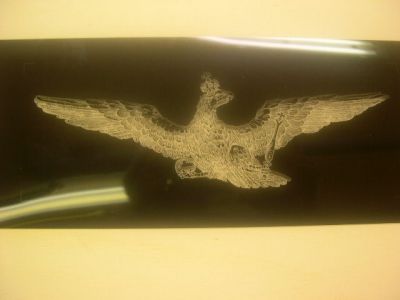
Ich studiere visuelle Kommunikation in Bern. Heute haben wir den Auftrag bekommen uns ein beliebiges Forum aus dem Netz zu nehmen und es in die Form eines Buches zu bringen (wird natürlich nicht veröfentlicht!). Da hab ich mich mal umgeschaut und dieses Forum als passend empfunden.
Nun denn. Wenn jemand Lust und zu viel Zeit hat, kann er mir eine Buchcover gestalten. Ich stelle mir natürlich eine typografische Umsetzung vor. Als super mega Belohnung stelle ich dem besten ein Buchexemplar zu. :-)
Würde mich über Ideen freuen!!
:shock: WÄre das nicht eher Deine Aufgabe?
Nein, wir wurden auserwählt, das ist jetzt unser Problem ...
Im Ernst: Die Idee finde ich interessant (wobei ich nicht genau weiß wo man da anfangen und aufhören soll. Ein klassisches Buch ist ja meistens etwas Abgeschlossenes).
Man könnte natürlich hier die spannendsten Diskussionen zusammentragen und diese in Buchform bringen. Das wäre wohl am lohnenswertesten.
Zum Cover: wenn du, Benjamin, hier Entwürfe reinstellst werden sie sicher kommentiert werden. Aber machen wird dir das wohl kaum jemand.
Spaß bei Seite.
Welchen Umfang soll das Buch denn haben?
Ansonsten finde ich die Idee ganz interessant.
Ein Querschnitt aus einem Fachforum, ordentlich mit Quellen versehen (ja, ich weiß, ich wiederhole mich) und einige der ja durchaus manchmal spannenden Diskussionen aufzeigend... warum nicht.
Ich könnte einen Andruck bzw. einen Negativ-Film von einem Kaiser-Adler mit Krone beitragen...
Oder, wenn Euch das zu wuchtig ist... mir schon, ich bin ja kein Monarchist... dann fallen mir bestimmt noch einige andere nette Entwürfe ein :)
Aber die Frage ist natürlich berechtigt:
Warum machst Du die Gestaltung nicht selbst?
slanted druckt ja auch immer einen teil ihres blog im mag ab,
ich finde das eher uninteressant, vorallem weil immer solche
blöden unbrauchbaren kommentare von xxx und mir dazwischen
stehen.
den titel machst du mal schön selbst und zeigst ihn uns danach,
wir müssen das immerhin absegnen.
Alle Quellenangaben werden drin sein und natürlich werde ich euch auch eine digitale Version ins Netz stellen!
Das Buch soll einen Umfang von 100-200 Beiträgen haben. Also nicht sehr gross. Den Dozenten geht es in erster Linie natürlich auch nicht um den Inhalt sondern um die Darstellung. Wegen dem Buchcover, ist wohl wirklich meine Aufgabe obwohl der Negativ-Film von einem Kaiser-Adler mit Krone gefällt mir schon ganz gut. Aber das kann doch noch nicht alles sein. :-)
Höhö...
Geschickt gemacht. Du spekulierst jetzt darauf, daß die Jungs hier ums Verrecken vermeiden werden, daß Dein Typoforum-Buch einen schönen, nationalen Charakter bekommt und deshalb Gegenentwürfe vorlegen, richtig? :twisted:
Leg' noch einen drauf und verwende für Deine Gestaltung die Tannenberg. Wenn Du dann die Diskussion "Schaftstiefel-Grotesk" für den Grundtext verwendest, hast Du etwas schön polarisierendes...
So als Ansatz: setz einfach alle Mitgliedernamen auf'n Titel – sind ja bloß so 3163 … Trennen tät' ich sie mit dem Klammeraffen. Und groß in der Mitte: Bleißetzer. So zur Zusammenfassung/Reduktion aller Diskussionen. (Mei, das setzt was!).
Die Idee ist allerdings weder neu noch einzigartig. Die Swissair (der Chef hab' sie selig) hat mal auf einem Geschäftsbericht mit mehreren Umschlagseiten sämtliche Mitarbeiternamen publiziert. Und meine Wenigkeit ließ in einem 9-Meter-Schaufenster eines Raiffeisenbank-Neubaus (Domat/Ems GR) alle 4000-irgendwas Familien-Namen der fünf Gemeinden im Einzugsgebiet der Bank als Sichtschutz aus Folie schneiden ...
gelesen werden. :-)
Wer kann mir weiterhelfen? Ab welcher Schriftgrösse kann eine Schrift nicht
mehr enziffert werden, ist jedoch immer noch als Schrift zu erkennen?
Sagen wir mal bei der Helvetica.
Naja, Helvetica wurde standardmäßig ab 6 p gegossen.
Ist aber sicher bei einem korrekten Druck bis 4 p runter noch gut lesbar.
Ganz schnell nur: die SAir-Group arbeitete damals mit irgendwas ganz knapp bei einer 4-Punkt-Schrift ...